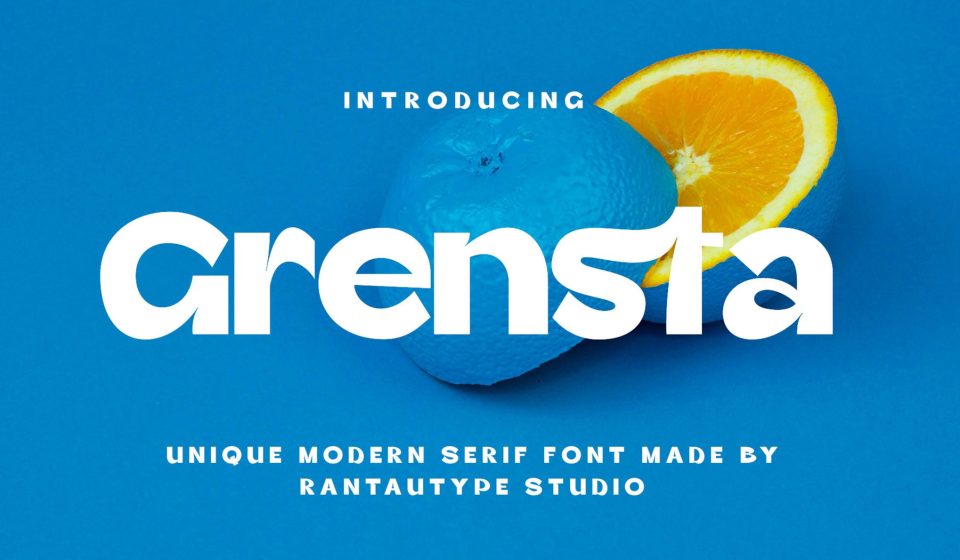
فونت Grensta – تایپفیس مدرن، جسور و با اصالت برای برندینگ و طراحیهای لاکچری
در دنیای طراحی مدرن، انتخاب یک فونت با هویت بصری قوی میتواند اعتبار برند شما را دوچندان کند. فونت سانسریف مدرن و شیک مدل Grensta، مجموعهای با کاراکترهای منحصربهفرد است که با استایل ضخیم (Bold) خود، حس اعتمادبهنفس و قدرت را به مخاطب منتقل میکند. این فونت انتخابی بینقص برای پروژههای خلاقانه، طراحیهای سبک زندگی (Lifestyle) و هر آن چیزی است که به لمسی از مدرنیته و ظرافت نیاز دارد. 💎✨
Grensta به گونهای طراحی شده است که در عین سادگی، شخصیتی متمایز داشته باشد. فونت انگلیسی برای لوگوتایپ و برندینگ شرکت Grensta برای خلق لوگوتایپهای حرفهای، تبلیغات بصری، واترمارک روی عکسهای باکیفیت، ست اداری و برندینگ محصولات لوکس فوقالعاده عمل میکند. این تایپفیس با هندسه دقیق خود، در صفحات مجلات، دعوتنامهها و پروژههای شرکتی، تصویری مقتدر و صیقلخورده از برند شما ثبت میکند. 🚀💼
ویژگیهای کلیدی و برجسته فونت Grensta
این فونت با تمرکز بر تعادل میان ضخامت و فرمهای مدرن، ویژگیهای زیر را ارائه میدهد:
- استایل Bold و مقتدر: ایجاد ضربه بصری قوی در تیترها و عناوین اصلی. ✅
- اشکال منحصربهفرد کاراکترها: طراحی خلاقانه حروف که باعث تمایز متن از فونتهای استاندارد میشود. 🏗️
- پشتیبانی از Alternate و Ligature: برخورداری از حروف جایگزین و ترکیبی برای خلق تایپوگرافیهای سفارشی. 🎨
- خوانایی بسیار بالا: حفظ وضوح در چاپ و نمایشگرهای دیجیتال. 📱
- تطبیقپذیری بالا: مناسب برای طیف گستردهای از پروژهها، از بیزینسهای سنتی تا استارتاپهای تکنولوژی.
کاربردهای اصلی فونت Grensta ⚙️
این تایپفیس برای طراحانی که به دنبال خروجیهای Pixel-Perfect هستند، گزینهای مقتدر است:
- طراحی هویت بصری و لوگوی شرکتهای معماری، مد و تکنولوژی 🏙️
- خلق واترمارکهای ظریف و حرفهای برای عکاسان و هنرمندان 📸
- طراحی بستهبندی محصولات آرایشی، بهداشتی و اکسسوریهای لوکس 💄
- استفاده در تیترهای اصلی مجلات لایفاستایل و بیلبوردهای تبلیغاتی 🖼️
- طراحی کارت ویزیت و ست اداری متمایز برای برندهای شخصی 💳
نکته مهم: قدرت اصلی فونت Grensta در استفاده از “فضای منفی” و کنتراست رنگی است. استفاده از این فونت با فواصل حروف (Letter Spacing) کمی بیشتر، میتواند ظاهری بسیار لوکس و پریمیوم به برندینگ شما ببخشد که برای کالاهای گرانقیمت بسیار موثر است.